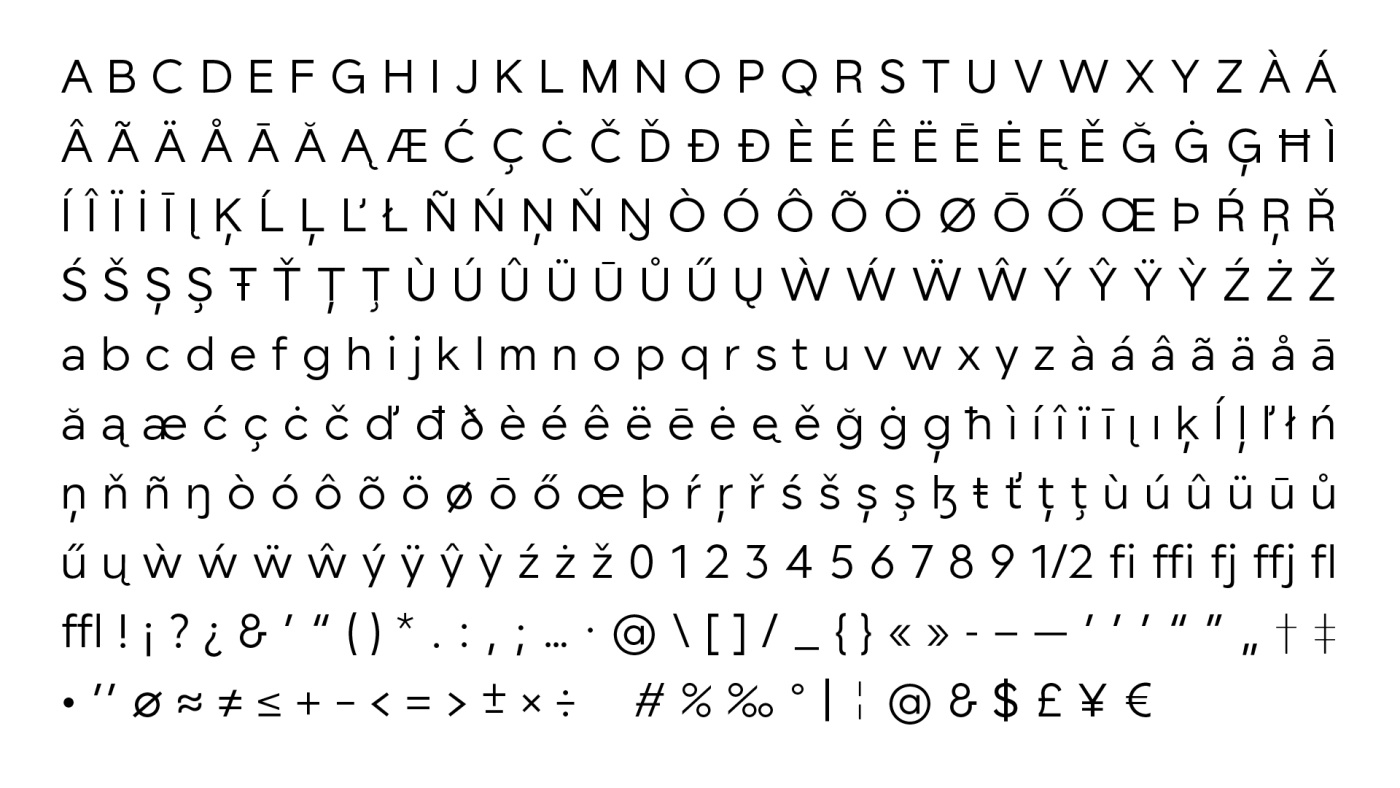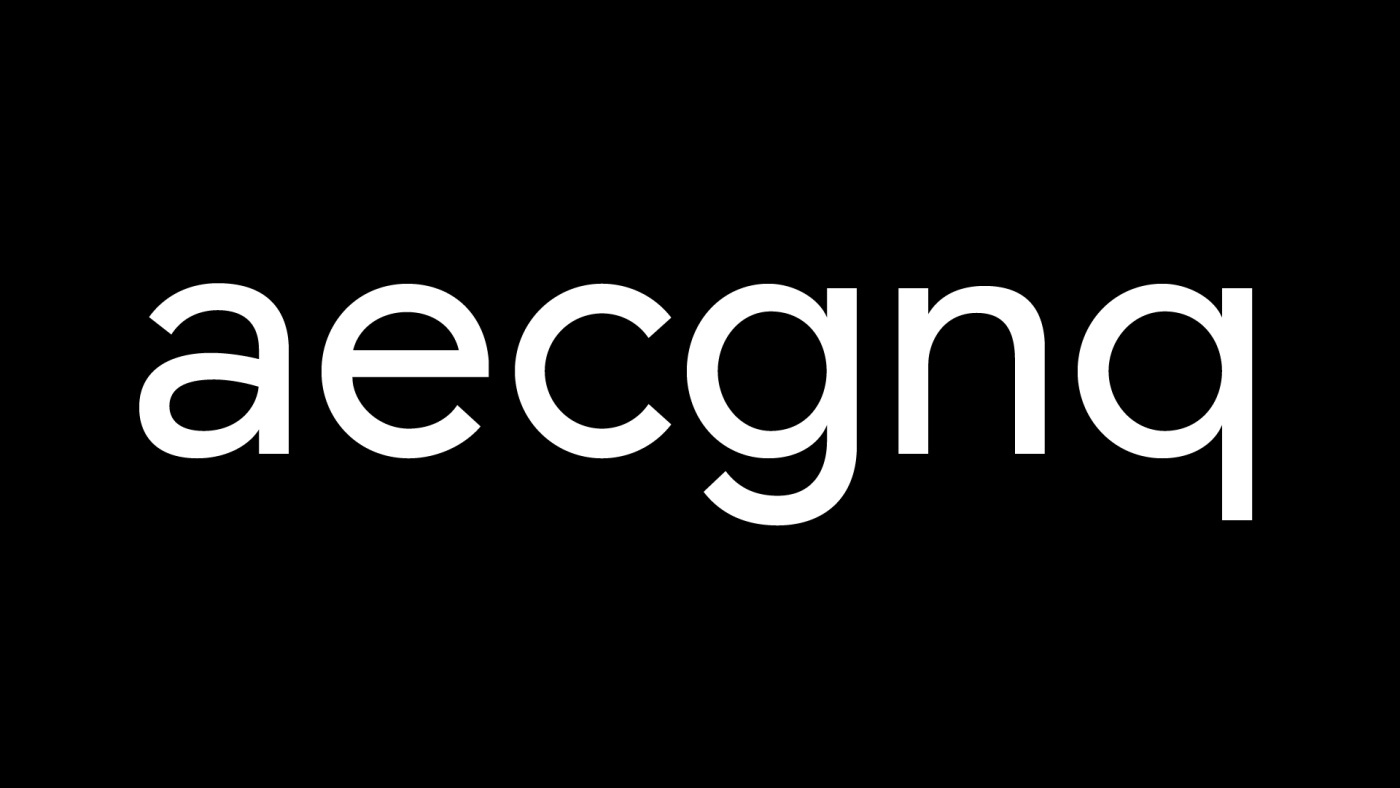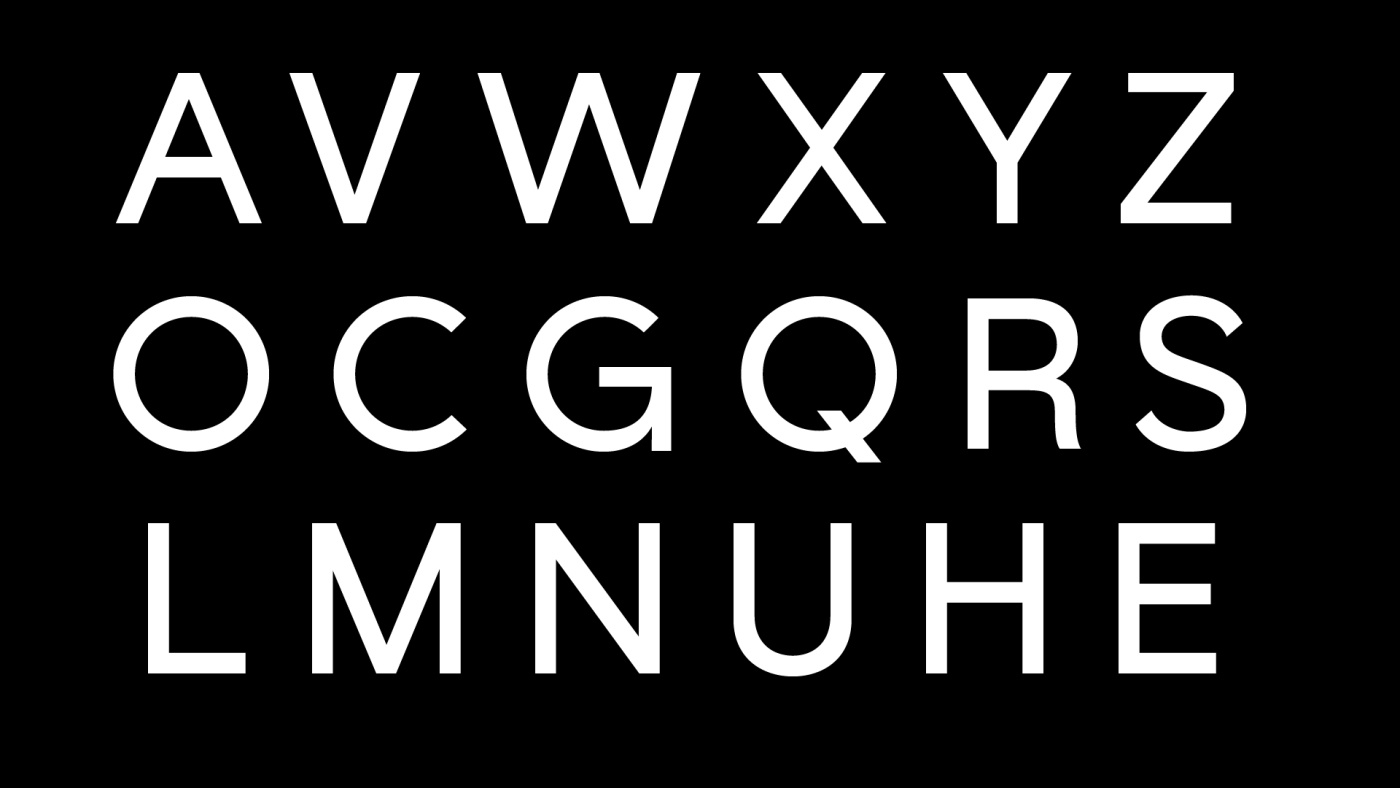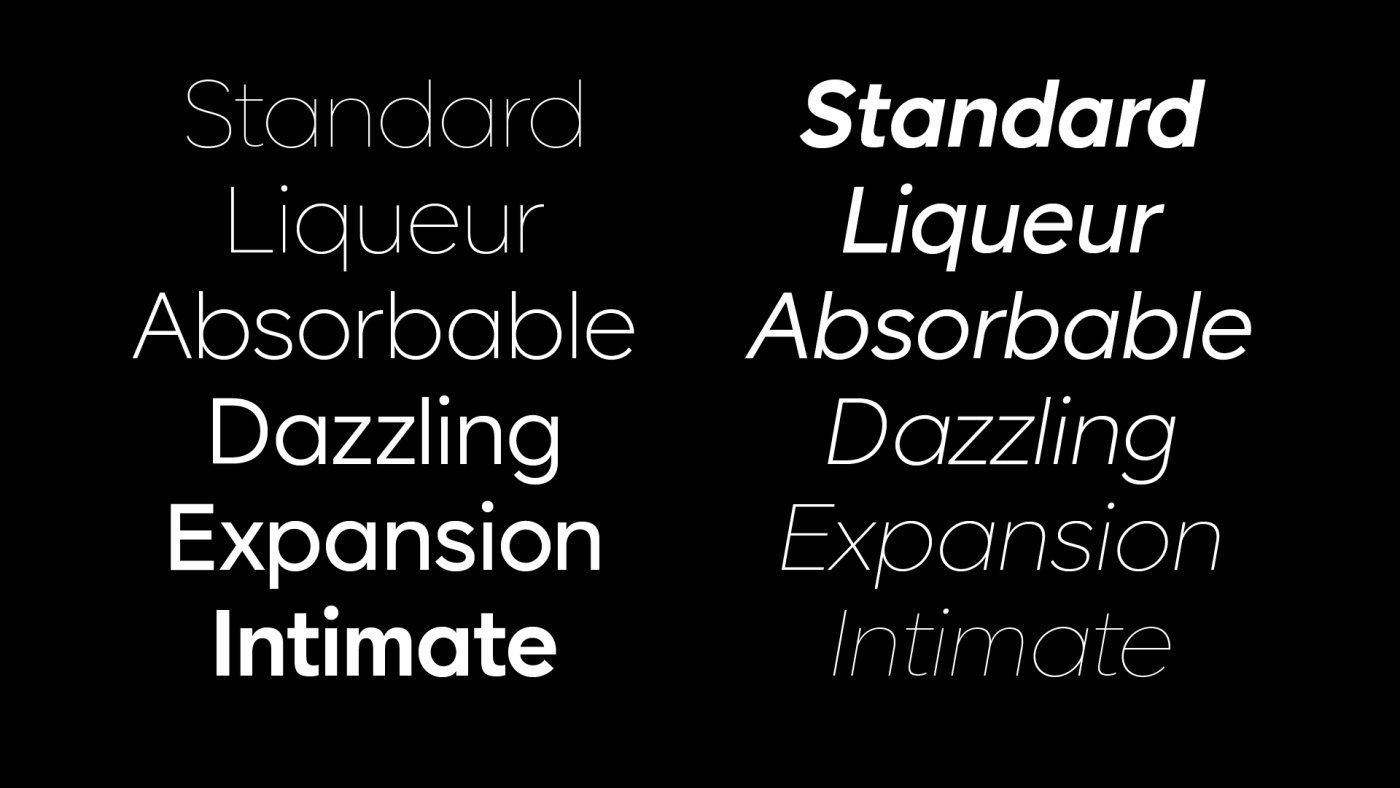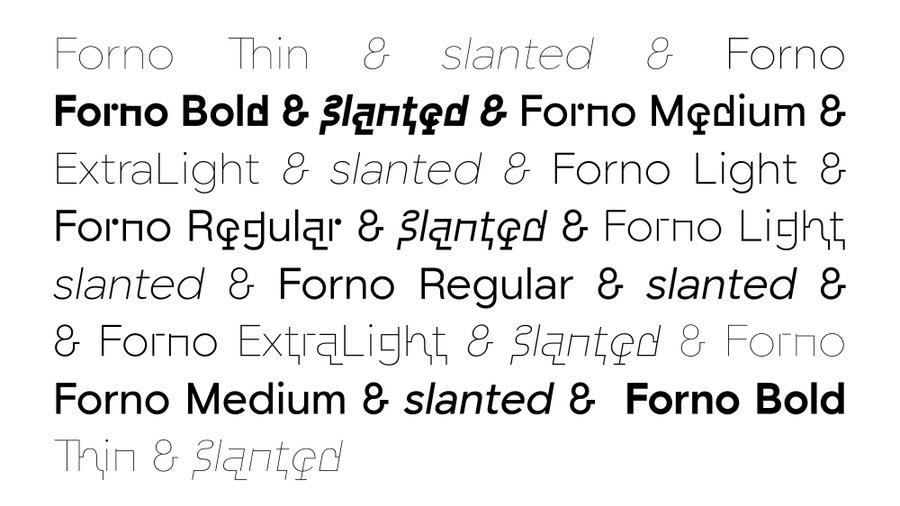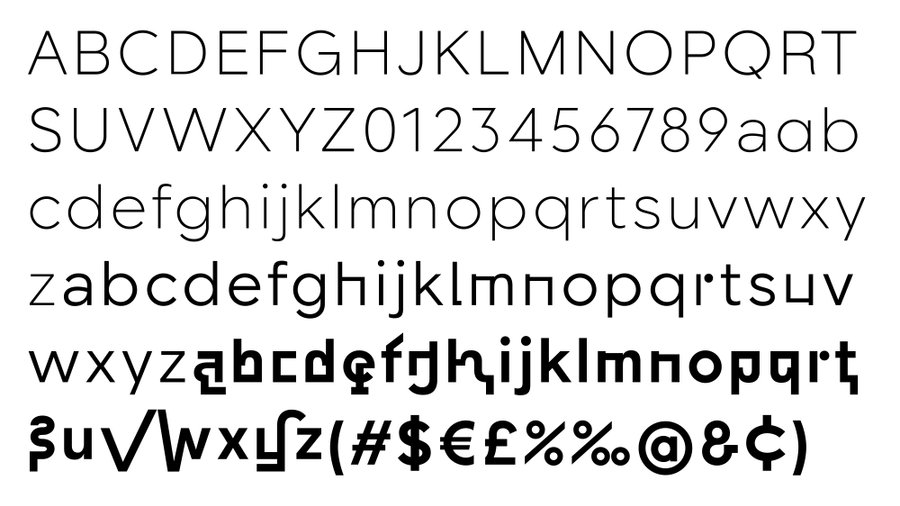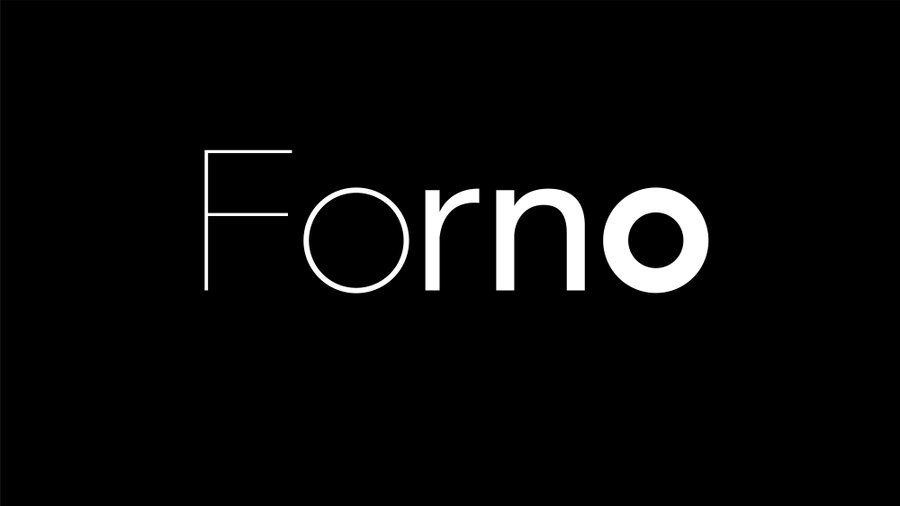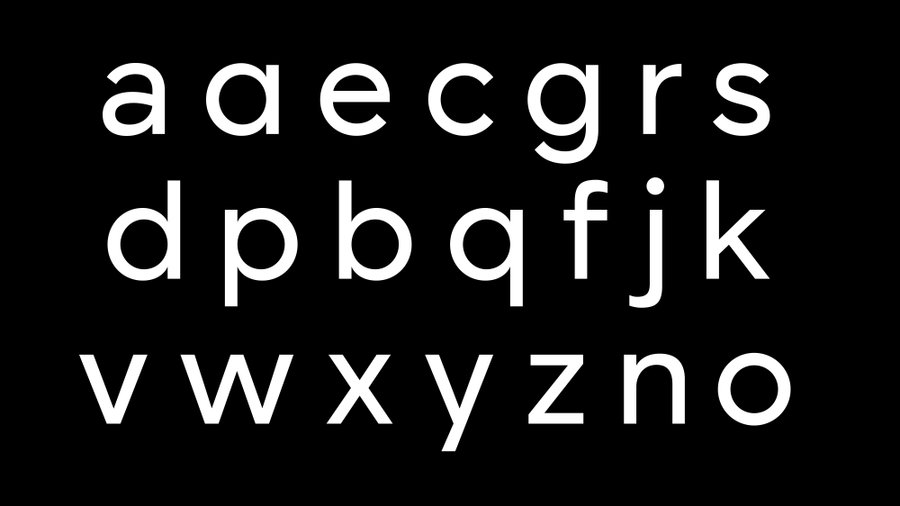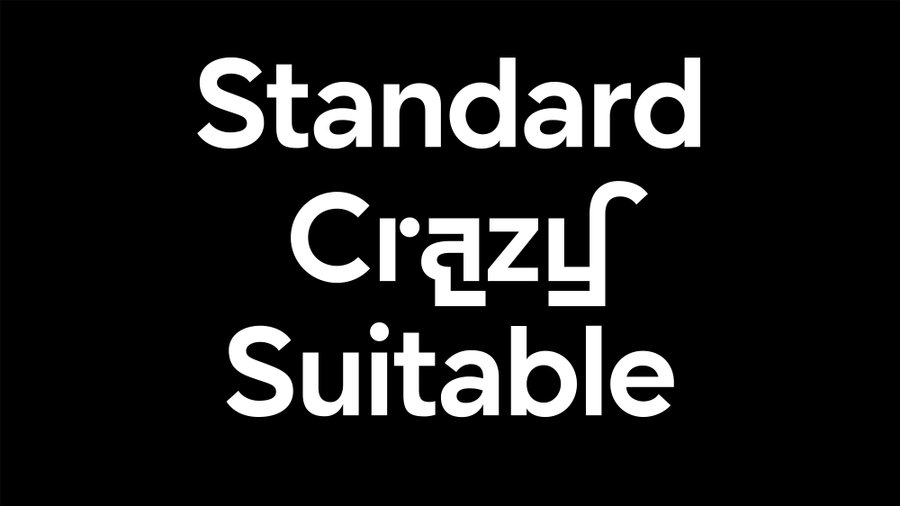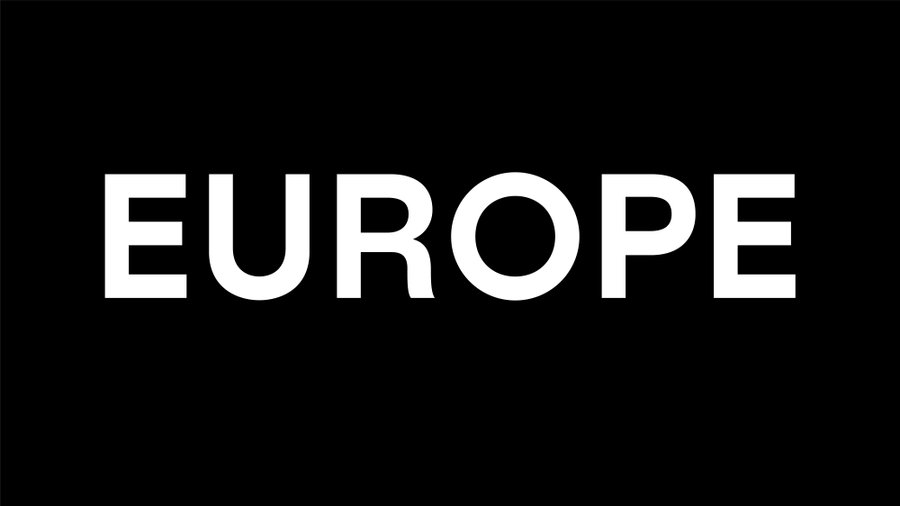
Forno Typeface
Forno est une famille typographique sans-serif au dessin géométrique.
Forno cache véritablement son jeu. Du plus standard et neutre au plus originale et perturbé, les 3 jeux stylistiques de Forno couvre un large choix de caractères. Dessinée dans la lignée des linéale géométriques, elle va jusqu'à reprendre certaine caractéristique du Futura.
La Forno s'étend du Thin au Bold et propose une version slanted.
Adrien Midzic
Adrien imagine, dessine et produit des lettrages originaux pour des exploitations en logo. Graffeur de "formation", il est devenu un excellent typographe et maîtrise parfaitement les rouages de la typographie moderne et y apporte avec subtilité la pointe d'originalité qui leur manquait.